提案我们只提供一个,你只有过和不过两种选择
在设计项目的方向已经确定,但结果还没有形成的模糊区域,每个设计师都在创造属于自己的宇宙。在这个时候,设计师可以自由的决定在什么约束条件下使用什么手段进行设计。
1993年,托马斯·威德肖温和尼基·冈尼森共同创立了thonik。他们的作品不遵循任何特定风格,不迷恋字体排印、印刷和构图等技艺。相反,他们的作品采用简单的形式,但背后是复杂的创作过程,通过对委托者的研究分析,进而设计出连贯完整的视觉形象系统。
在很大程度上,这是一种“懒设计”,也就是利用现有的资源适可而止。换种方式来定义这种手法的话,就是极简主义。
thonik 2017年 团队合影
thonik与客户的工作模式和我们日常的工作相反的,那就是他们工作室只提供一个提案用来回应客户,当然要是客户实在不满意,他们也会免费的提供第二个方案。
他们认为:“只提供一个提案,表明工作室的专业立场,是对客户的专业选择,客户所付的设计费大部分应该是基于设计师的判断力、专业知识,其中最重要的是设计师的选择,相反提出很多的提案给客户,会让设计师丧失专业的立场和专家的身份,变成了工具,结果是在人工智能与廉价设计的冲击下,设计师快速贬值。”
设计师简介
尼基·冈尼森 Nikki Gonnissen。thonik联合创始人和董事。2015年开始担任国际设计师联盟AGI主席。18年卸任,三年的任期内,革新了AGI让组织变的更年轻,更当下。
托马斯·威德肖温 Thomas Widdershoven。thonik联合创始人和董事。担任著名的荷兰埃因霍温设计学院院长,他策划了一系列的展览,探索和预测下一代设计师如何在不断变化的世界中定位自己。
作品解析
2002 / 阿姆斯特丹市 视觉识别系统
2002年,阿姆斯特丹决定重新设计自己的视觉识别系统。面对多年来各种市政单位、行政单位和专门机构所建立的多而混乱的形象标识。
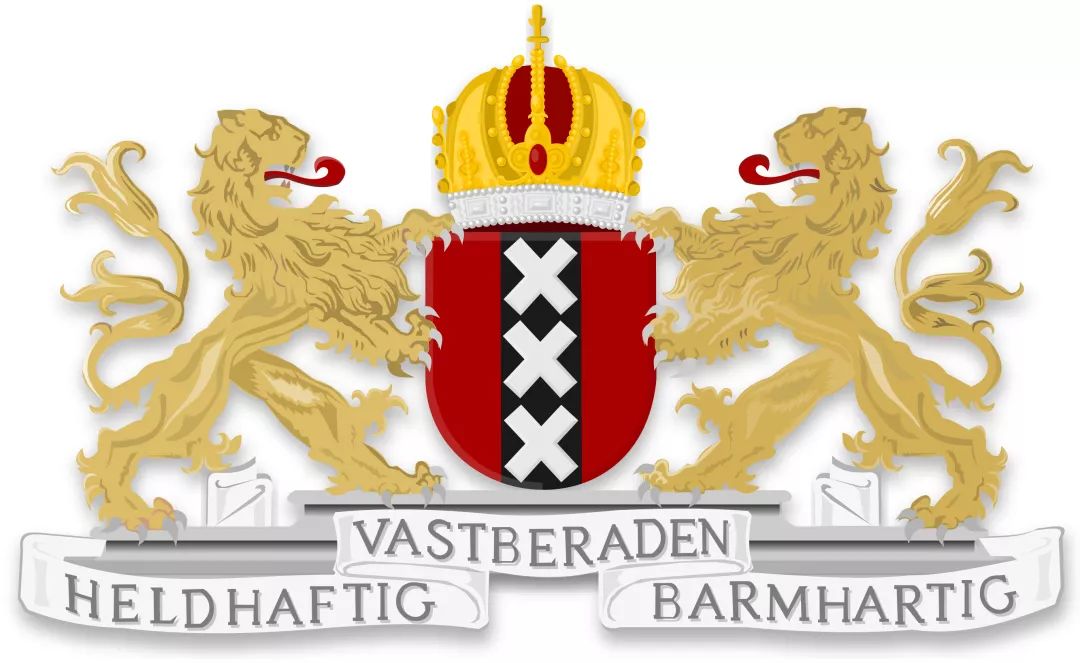
阿姆斯特丹市·城市标志
thonik在接手后,决定让整个市政回到市民所熟悉的中世纪标识。三个“叉”的竖向重叠,这个创意很简单,并且也是基于再利用而不是创新。这也是他们“懒设计”的体现。
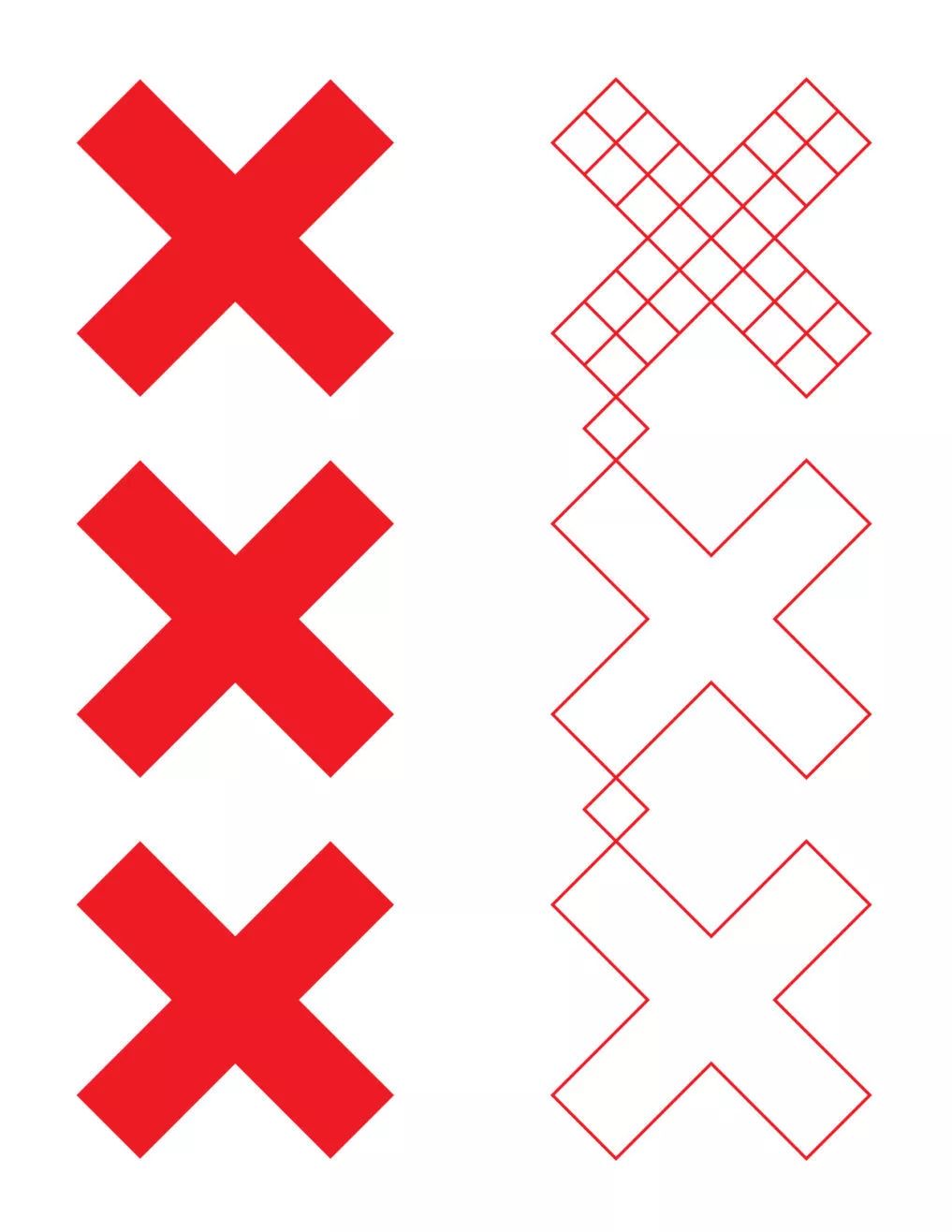
升级后·阿姆斯特丹市·城市标志
thonik市政府提出了一种清晰、开放、易懂的传达风格。这种开放的核心是釆用“三个叉”作为城市标识。象征了城市与公民紧密相连,代表了公民与政府的新平衡关系。
thonik所做的无非是通过清空周边视觉干扰来解放这个标识。他们的设计并不是为城市设想新的功能或形象,而是彰显城市的本真。
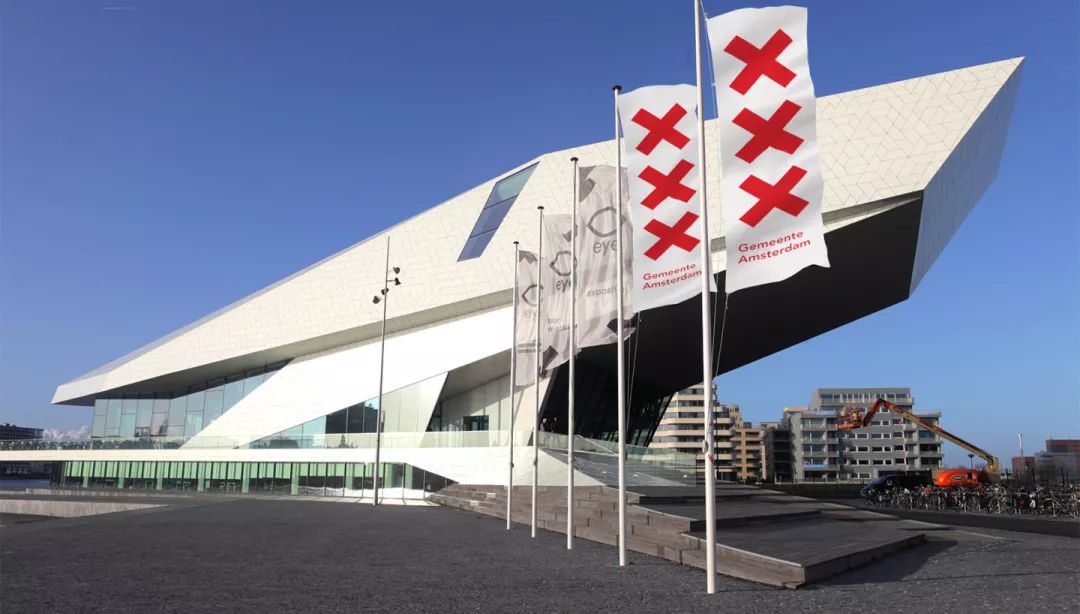
同时“三叉”也可以标示市政建筑及市政工程的位置所在。
这个“三叉”符号成为了一个运算符、或者说是一个催化剂,将城市理论的核心理念与城市的各个行政部门及机构连接起来。它仅仅只是重新激活了一个出现于中世纪的纹章。
👈重新升级后的市政物料
设计师几乎没有对图像进行任何的修饰,在许多方面它就是“懒设计”的完美范例:利用已有素材,解释其内在力量与作用,全力将它突出,别的尽可能少做。
2003 / 博伊曼斯·范伯宁恩博物馆
在为鹿特丹的博伊曼斯・范伯宁恩博物馆,重新升级的时候。thonik受到了兰斯·怀曼在1968年为墨西哥奥运会的平面设计启发。
👈 1968年 墨西哥奥运会的相关资料
博伊曼斯·范伯宁恩博物馆采用了新的标识,其字体与墨西哥奥运会的字体相似。两年后,馆长 SjarelEx认为这个标识不适合博物馆。三条线的字体使博物馆的名字几乎看不见。但thonik建议继续使用这一字体,也赋予了它独特的风格。
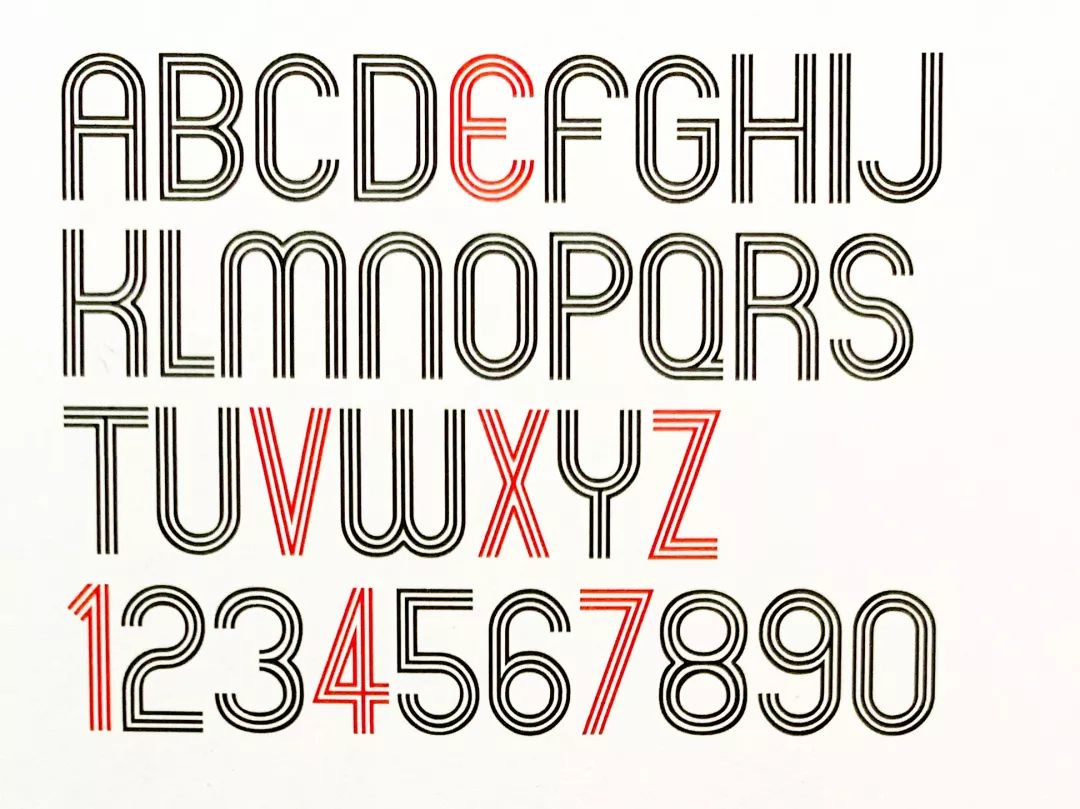
1968年 兰斯·怀曼设计的字体
重新设计后的字体
thonik将字体放进网格内,去掉了原来的斜线。调整了粗细比、笔画和颜色。让这套系统重新充满了可能性,在2003-2013这个期间,一共设计出了300个展览的邀请函和海报。
👈重新升级后的博物馆物料
2005 / 荷兰社会党
很少有设计公司会主动的参与到政治中去,在之前thonik,在给政府机关服务的过程中,给了他们机会可以参与反思这些机构应当如何在社区能更好的实现自我。所以当他们参与荷兰社会党(SP)的时候,才真正使他们得以用设计去创造一个新的角色。
荷兰社会党标志
在合作的初期,荷兰社会党他们只是需要重新设计党标以应对竞选,但是很快thonik就变成选举智囊团中的一部分了。
而thonik的想法也很简单,就是将西红柿代表这个政党,原因是其他的政党一般都选用玫瑰,玫瑰就代表着他们高冷的特性。而西红柿就相对来说很亲民,并且还可以用来扔向当权者。
通过设计将西红柿转化成为一个抽象符号,就如同苹果公司那个象征原知及原罪的标志一样。同时为他们设计了一个全新的标语“NU SP”这个政党就给人一种很亲民,很有活力的感觉。
thonik还帮助他们设计了一系列的周边产品,包括塑料的汤碗、红领巾甚至是可以帮你擦掉家中所有政治污垢的清洁海绵。
接着竟然为荷兰社会党设计出了一辆车,你能想象嘛?一个政党的候选人不是在演讲,竟然是在给你分发西红柿汤?
thonik为荷兰社会党制作的病毒小视频
最后thonik还为他们,拍摄了病毒小视频,出演的主角就是当时的荷兰社会党的一把手。
在荷兰的全国竞选中,地方选举的中心“这里HIER”作为“更好的荷兰从这里开始(A better Netherland starts HERE)”这句话的一部分。
任何宣传活动,不管宣传产品还是政党,成败的原因终归不可知,但是一些列活动下来,荷兰社会党从一个边缘政党成为了荷兰第三大党。似乎是有理由相信thonik是这一成功的重要因素。
2006 / 阿姆斯特丹公共图书馆
在接手阿姆斯特丹公共图书馆的项目时,thonik认为图书馆作为一个至关重要的民主机构,向公众提供接触知识和媒体的途径。公共图书馆现在面临着信息时代的困境,图书已经大部分数字化。而信息基本上可以做在网络上找到,阅读已经从书本变成了声音。
阿姆斯特丹公共图书馆的标识由小字号的“ openbare(公共的)和“ Amsterdam”(阿姆斯特丹),以及横向放置的大字号的“ bibliotheek”(图书馆)组成。缩写oba,o和a旋转了90°,呼应了这一系统。
这个想法很简单,通过将其应用到所有官方交流中,语言本身就是徽标,这对于像图书馆这样的以语言为导向的机构来说非常合适。
导视系统这个部分有一个很突出的设计,就是将标识的文字排版与建筑内的各个部门和指示牌联合起来。
2017年7月7日,图书馆新馆正式对外开放,这是thonik为开幕设计的海报。
👈重新升级后的图书馆海报
2007 / 阿姆斯特丹艺术大学
阿姆斯特丹艺术大学(Amsterdamse Hogeschool voor de Kunsten或AHK)是艺术教育学院的集合。由六个不同的机构组成,他们需要一个既可保留徽标又可更改名称的系统。
这个时候thonik,提出的方案是“一所学院:六个系一个徽标:六种颜色”其实就是一套标志通过更改颜色来代表不同的学科。
👈重新升级后的标志
新的身份使阿姆斯特丹艺术大学及其六个学院具有可见性和可识别性。一个符号,两个完美的圆向右偏移,位于底部。每个教职员工都通过自己的颜色清楚地识别。其特点是,教职员工的名称保持黑色,而主要机构的名称适应其颜色。
2008 / 威尼斯建筑双年展
2008年的威尼斯建筑双年展,主题是“建筑之外的建筑out there: architecture beyond building”
thonik从一个代表地球的圆开始,之后增加了一个“小房子”,重复这个图形最终形成一个图案。
文字设计在图案上会改变颜色。场景设计中,我们把二维的视觉识別三维化。8个球高的“球墙”分隔了展览空间。黑球和白球的组合形成清晰的文字,引导参观者观展。
保持展览空间的开放性时,通过三维雕塑(引导参观者穿过展览空间的印刷墙)将二十个区域联系起来。